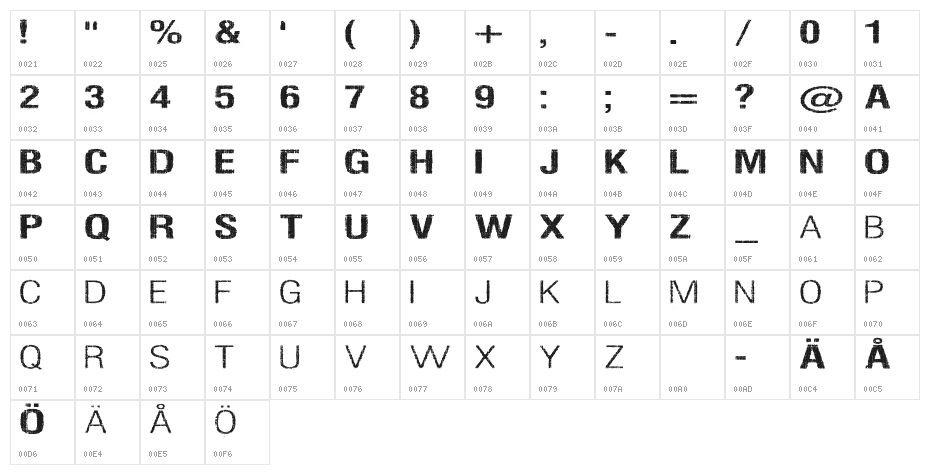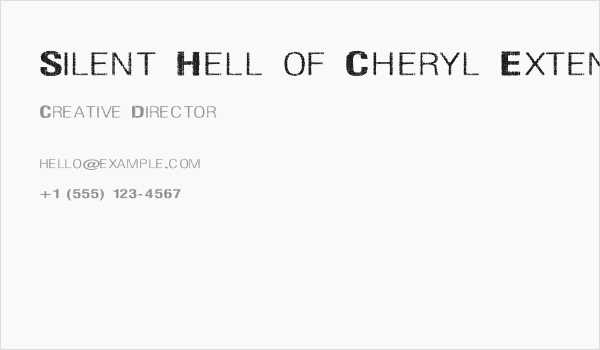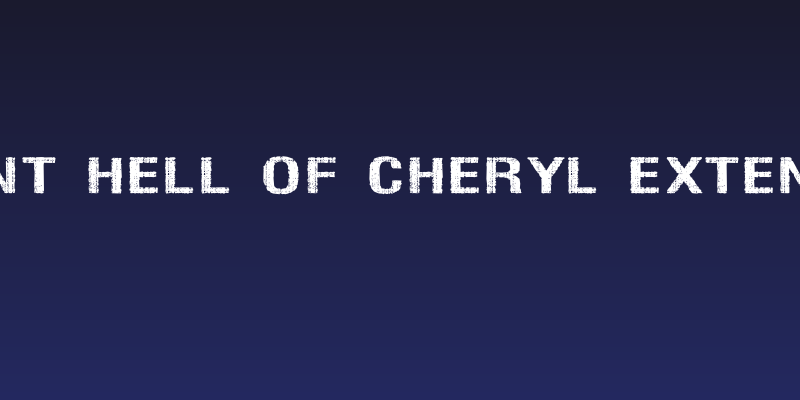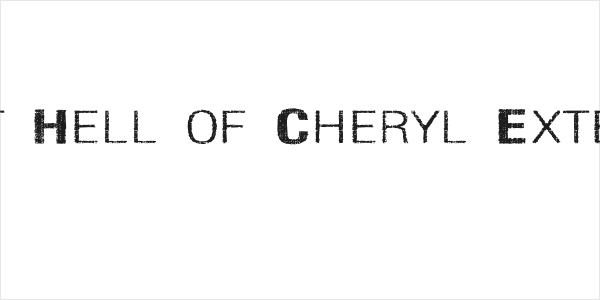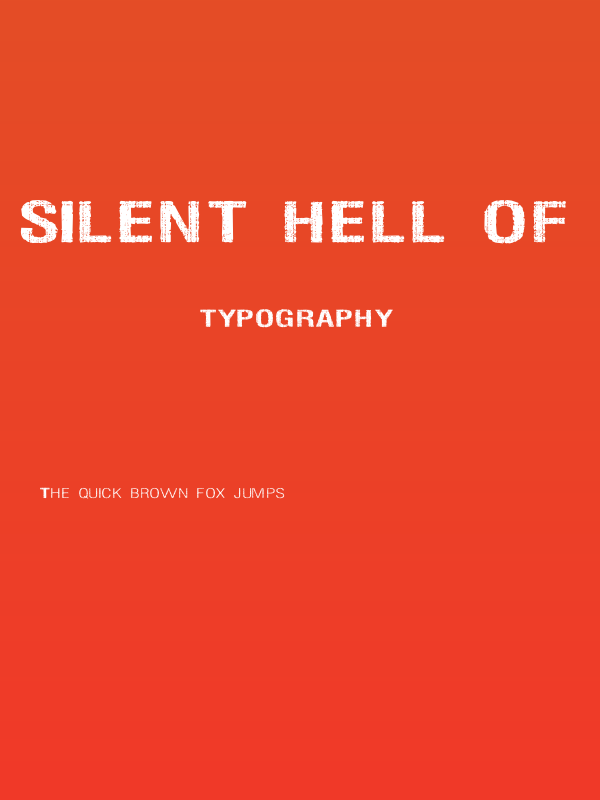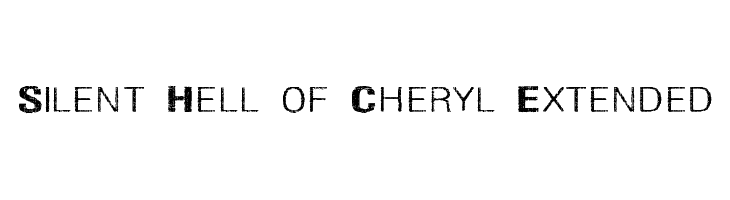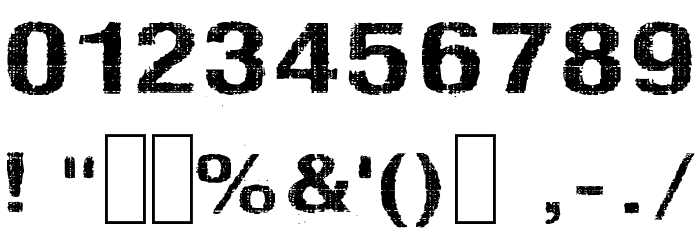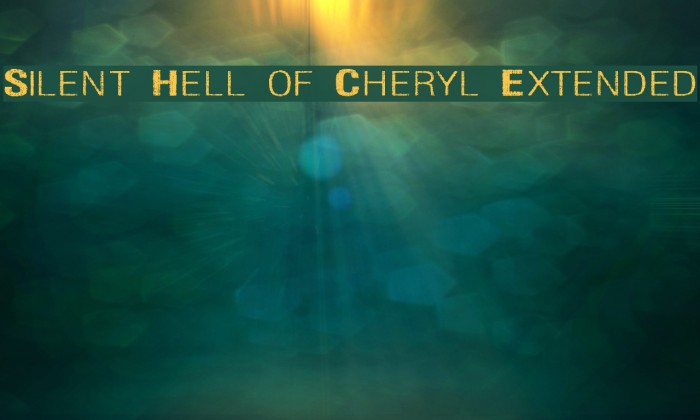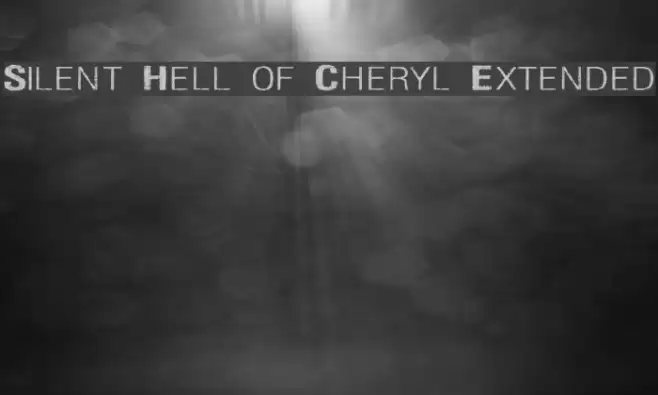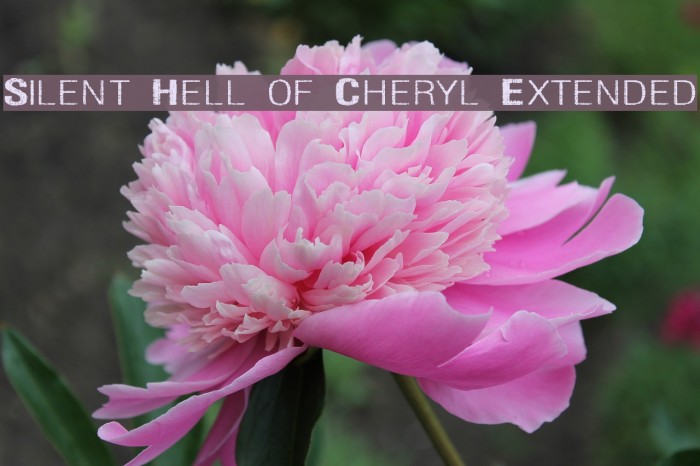
Silent Hell of Cheryl Extended Font
✎ Distorted Eroded
| Catégories | Distorted Eroded |
| Style général | Vintage, Grunge |
| Projets proposés | Ideal for album covers, posters, branding for edgy products, or any project needing a vintage, distressed look. |